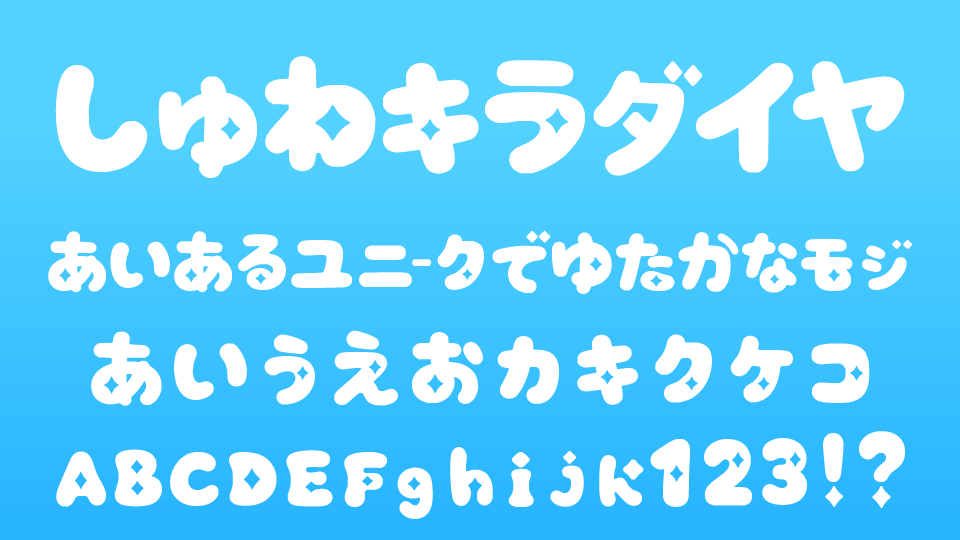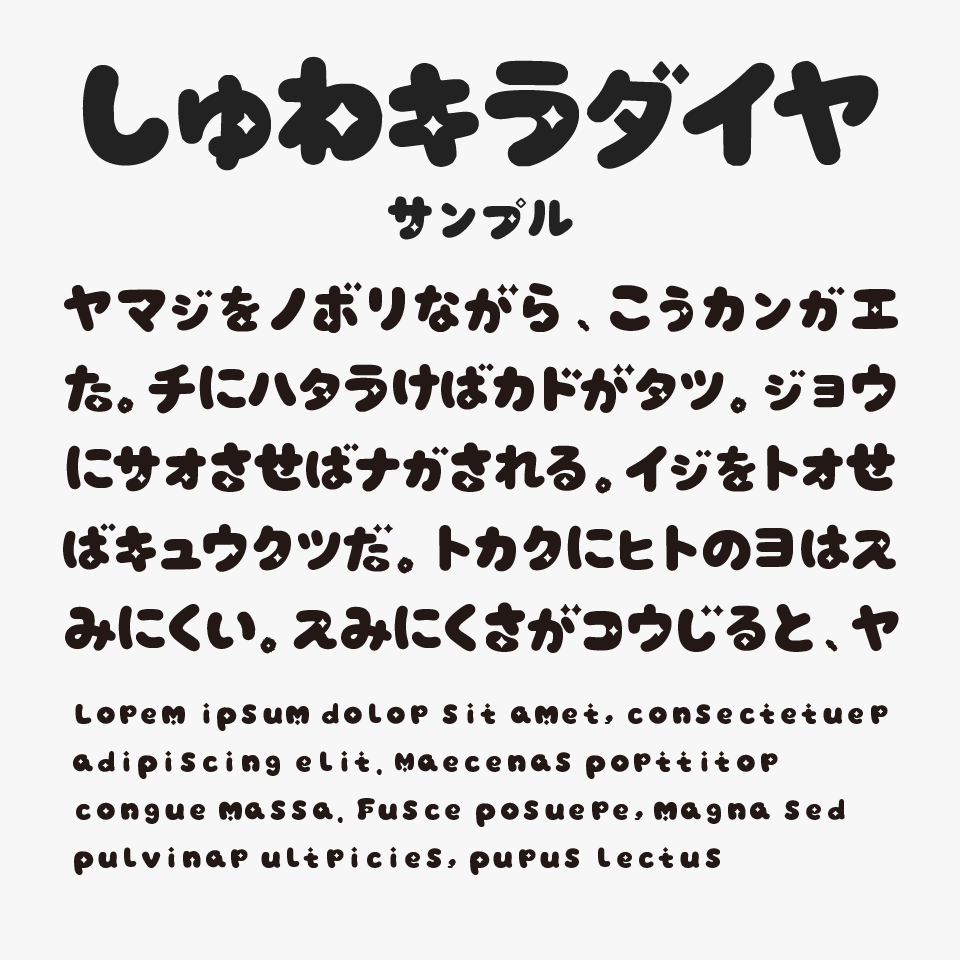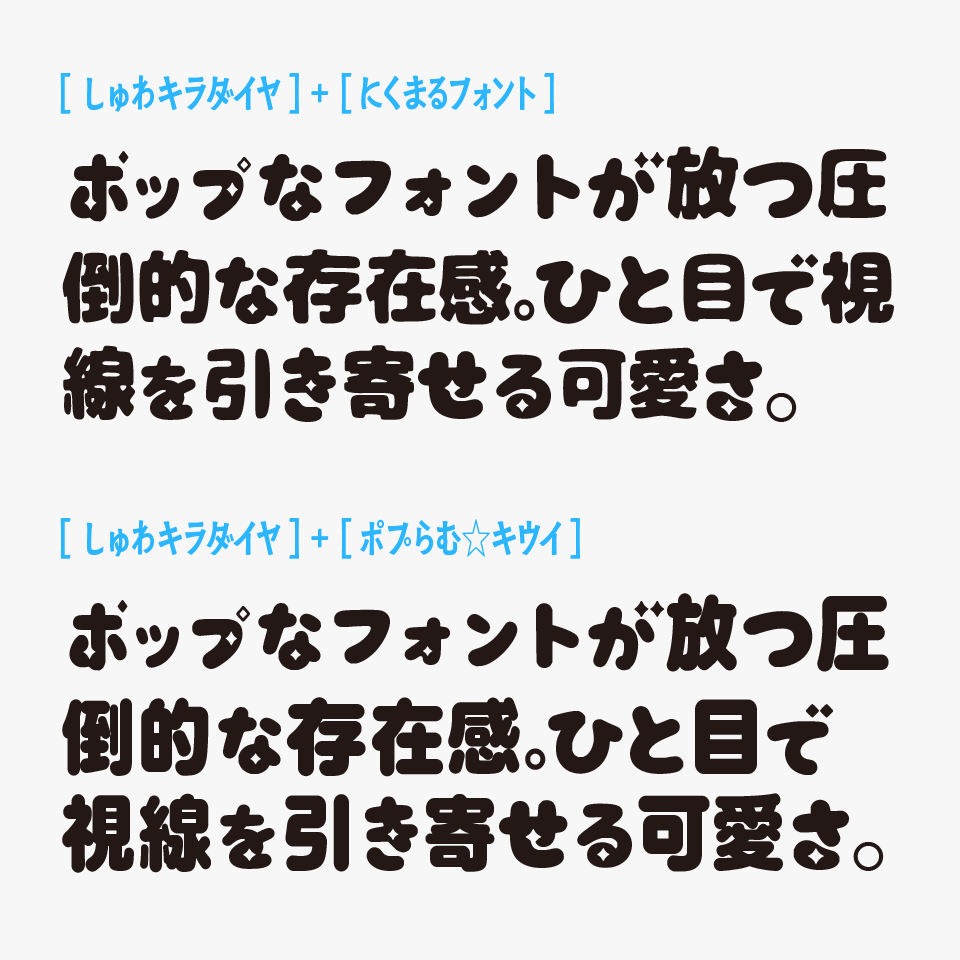
しゅわキラダイヤ
しゅわキラダイヤフォントは、手書き感のある丸みのある太字をベースにしながら、文字の一部に小さなダイヤのような装飾が散りばめられた、華やかで可愛らしいフォントです。
ぷっくりとしたシルエットが親しみやすく、全体に炭酸の泡が弾けるような軽やかさがあり、見ているだけで楽しい気分になれるデザインです。
アイドル風のロゴやVtuber配信サムネイル、キッズ向けデザインなどと相性が良く、デザインを一気に明るくしてくれるフォントです。
装飾が細かく入っていても読みづらさを感じにくく、タイトルや短文でもしっかり存在感を発揮します。
かな文字フォントなので、漢字は別のフォントと混植してみても面白いかもしれません。
収録文字は、ひらがな・カタカナ・アルファベット・数字・記号が収録されています。